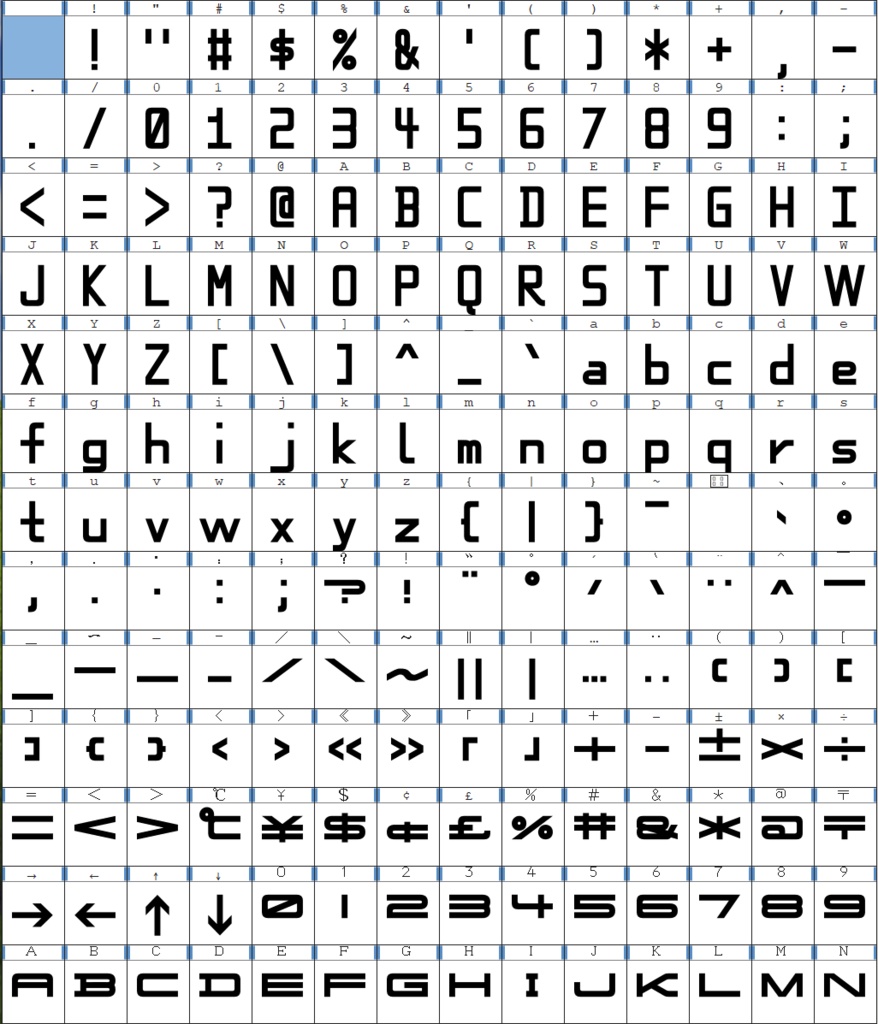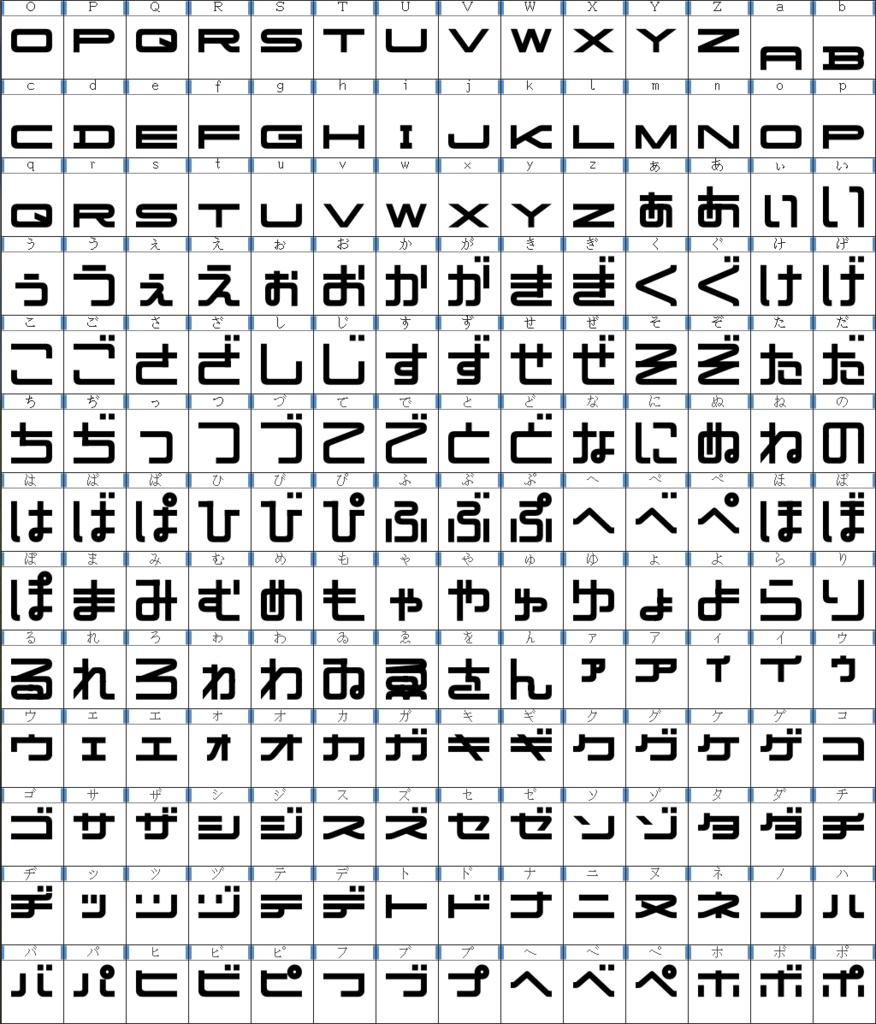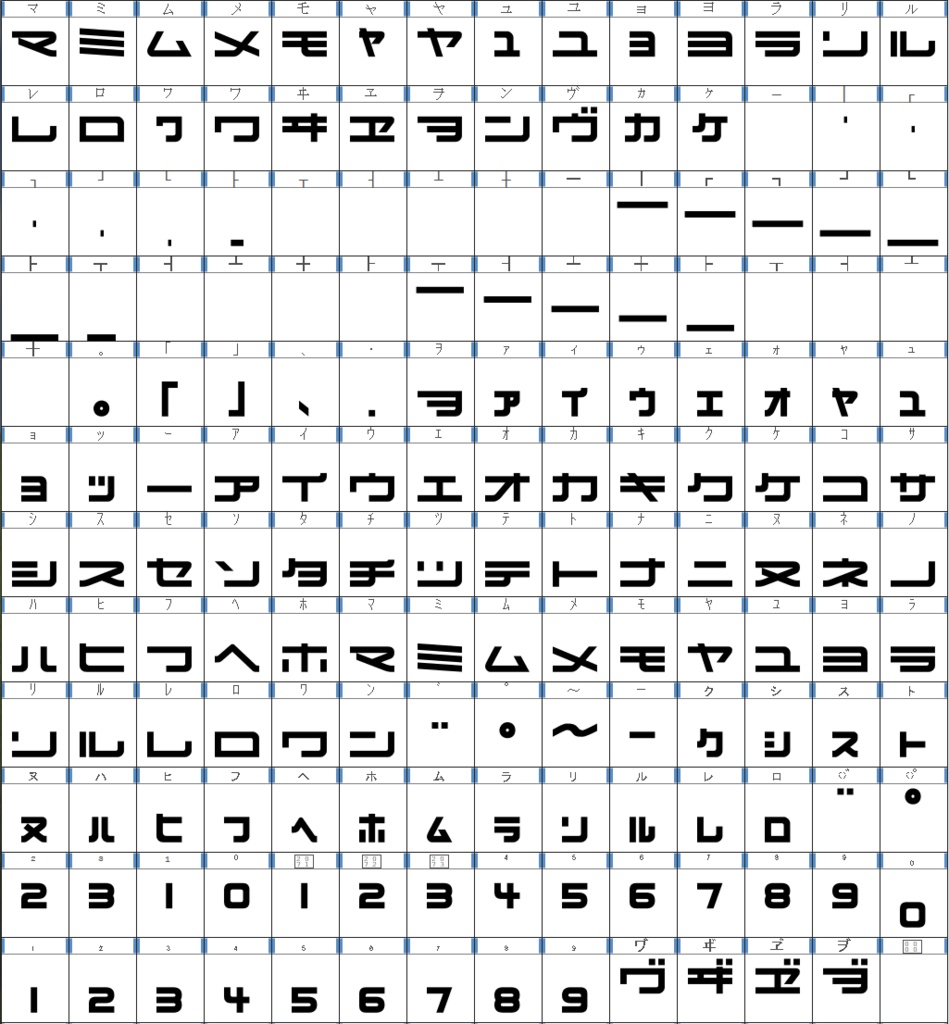
ロードスター(Road star)漢字なし版
「ロードスター」というフォントを公開します。 横長に書いたカタカナを全角のほうは上に、 半角のほうは下に配置したロゴタイプ向けフォントです。 収録文字:ひらがな・カタカナ・英数字(全角英字は大文字が横長で上に、小文字は横長大文字を下に、半角は比較的普通の字体で収録)・ 上付き数字、下付き数字。 また、罫線のほうには文字どうしを繋ぐための線を収録しました。 商用利用可能(自己責任)、反社会的利用禁止でお願いします。 また、視認性の下がらない程度の改変も自由にできます。
「ロードスター」というフォントを公開します。
横長に書いたカタカナを全角のほうは上に、
半角のほうは下に配置したロゴタイプ向けフォントです。
収録文字:ひらがな・カタカナ・英数字(全角英字は大文字が横長で上に、小文字は横長大文字を下に、半角は比較的普通の字体で収録)・
上付き数字、下付き数字。
また、罫線のほうには文字どうしを繋ぐための線を収録しました。